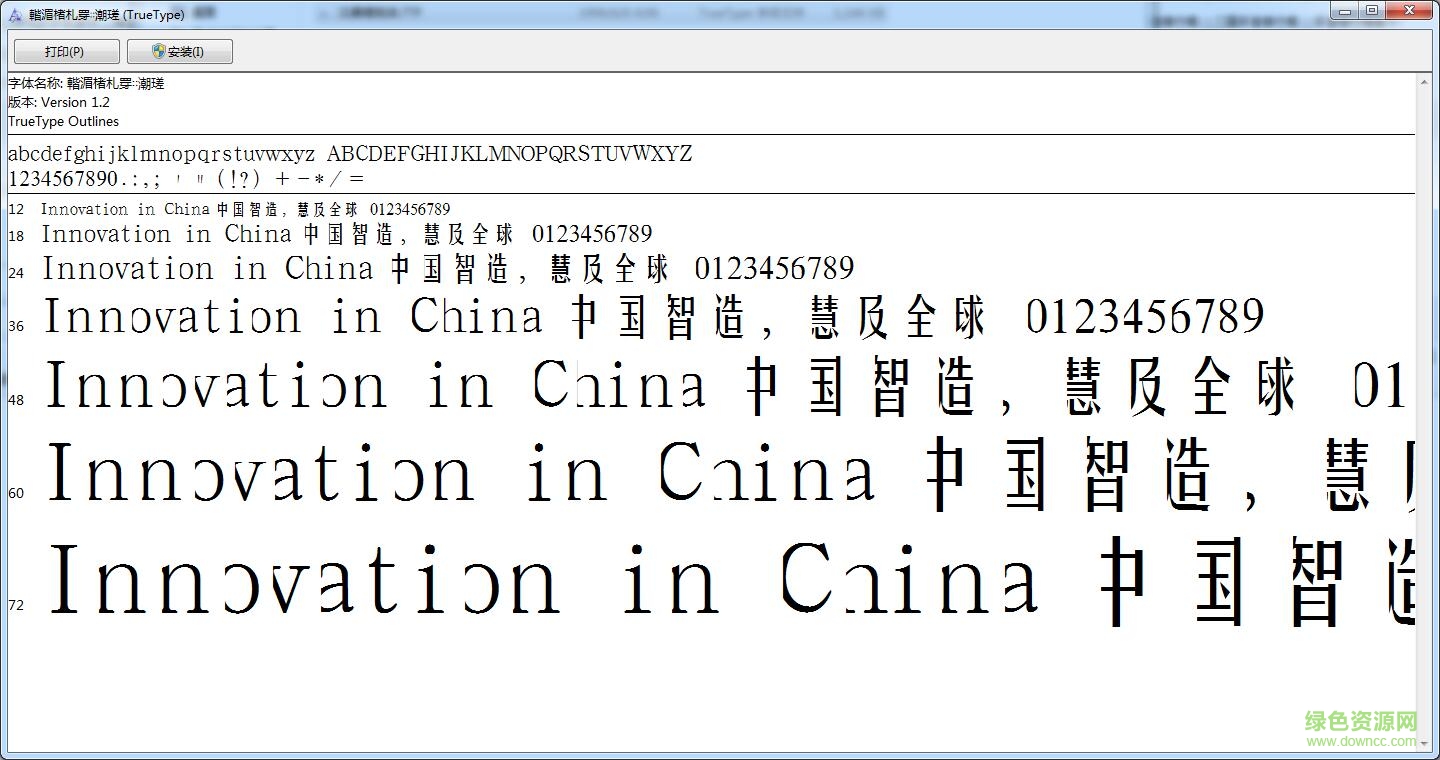
漢鼎簡(jiǎn)姚體是一款免費(fèi)的字體應(yīng)用!這款字體比較規(guī)范,字形偏長(zhǎng)!可以在多種windows系統(tǒng)下運(yùn)行安裝,其字體所表現(xiàn)的方式也比較特殊,一般很少遇見,只要專業(yè)的編輯人員才會(huì)使用,喜歡的朋友歡迎來綠色資源網(wǎng)下載。
漢鼎簡(jiǎn)姚體是一款端正、大氣的中文簡(jiǎn)體字體,姚體與宋體類似,不過字形更偏瘦長(zhǎng)設(shè)計(jì),而且字間距較大。需要商業(yè)用途的朋友要和作者聯(lián)系并取得授權(quán)。需要的用戶快來綠色資源網(wǎng)下載吧。